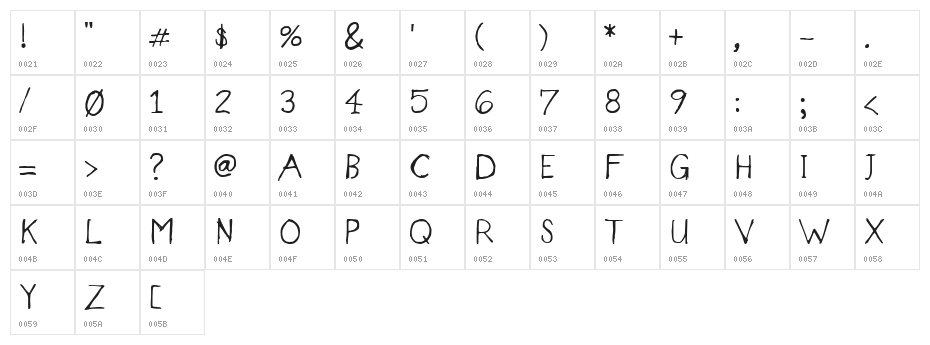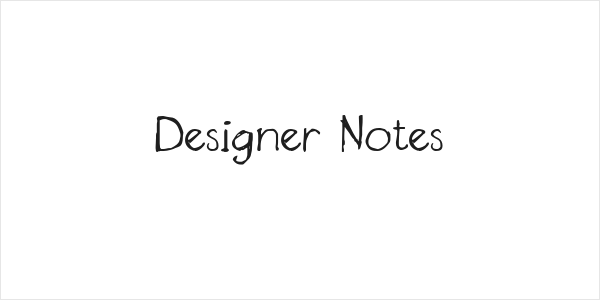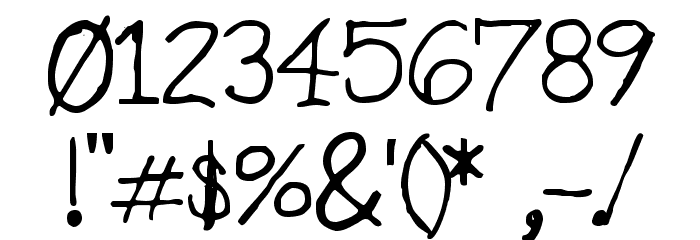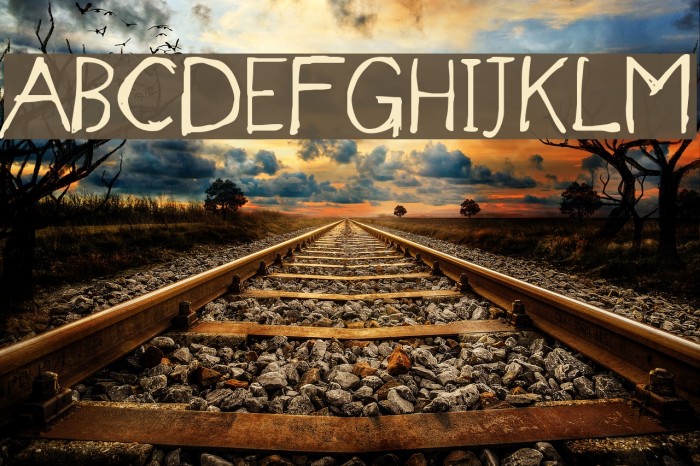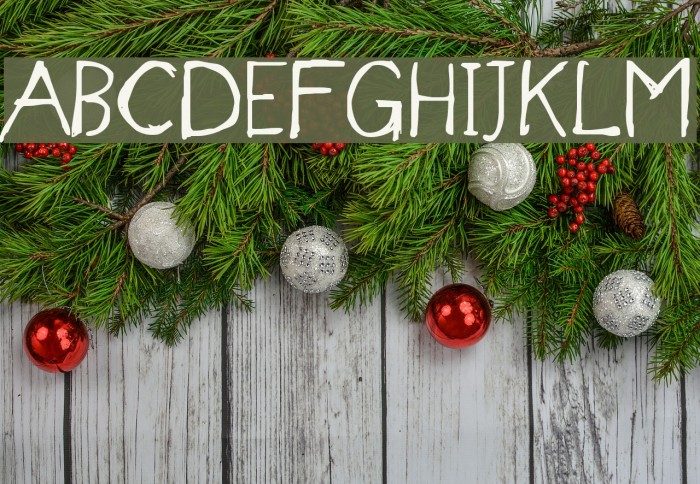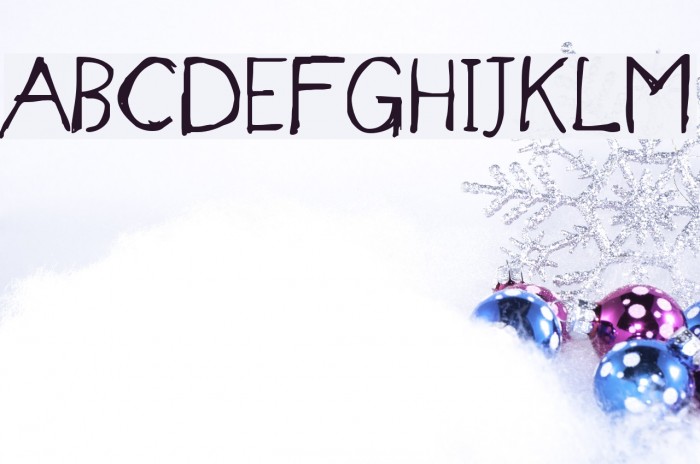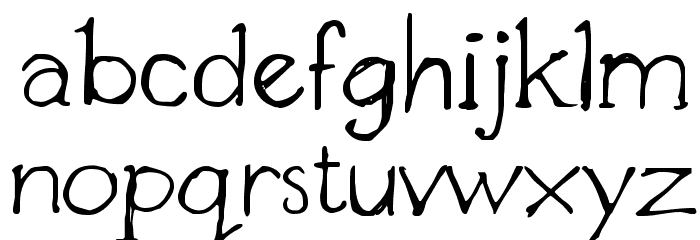
Designer Notes Font
| Style général | Casual, Organic |
| Cas d'utilisation | Logos, Invitations, Personal Notes |
| Projets proposés | Ideal for personal notes, creative invitations, casual branding, and artistic posters. |